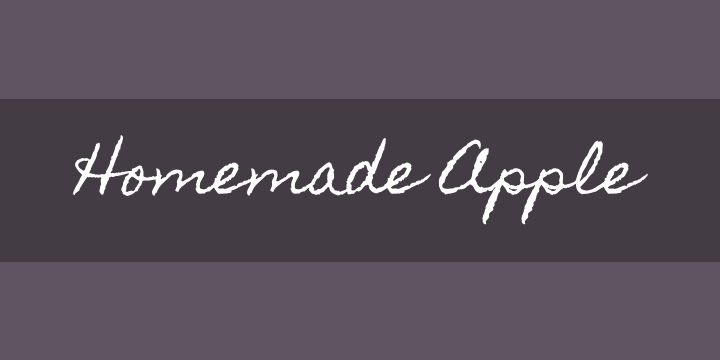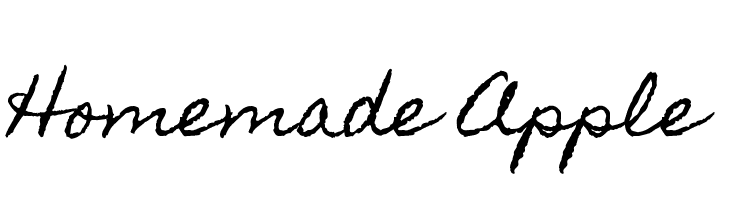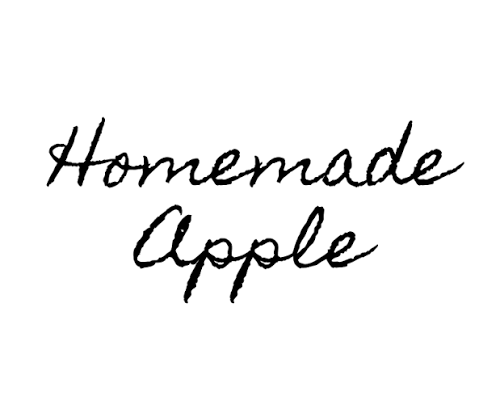
Nhiều phiên bản Homemade Apple Font trên Internet chưa được Việt hóa đầy đủ, dễ gặp tình trạng thiếu dấu tiếng Việt, sai ký tự hoặc đường nét chữ viết tay bị mất cân đối khi đưa vào thiết kế. Ngoài ra, các file font chất lượng thấp có thể làm chi tiết nét vẽ bị giảm độ sắc nét khi phóng lớn để in bao bì, tem nhãn hoặc sản phẩm nhận diện thương hiệu.
Homemade Apple font là gì?
Homemade Apple là một phông chữ thuộc dòng Script (chữ viết tay) được xây dựng dựa trên nét bút thực tế, mang phong cách mộc mạc, phóng khoáng và giàu tính cá nhân. Đặc trưng của bộ chữ này là các đường nét không quá trau chuốt, mô phỏng lại cách viết bằng bút dạ hoặc bút mực trên giấy nhám, tạo cảm giác thân thiện và gần gũi. Đây là sự lựa chọn phù hợp cho các dự án thiết kế yêu cầu tính “handmade” như nhãn mác nông sản, tiệm bánh, mỹ phẩm hữu cơ hoặc các thiệp mời mang phong cách Vintage.
Vẻ đẹp của homemade apple font nằm ở khả năng khơi gợi cảm xúc chân thành và truyền thống. Tuy nhiên, cấu trúc chữ có các nét nối tự do nên đòi hỏi quy trình xử lý kỹ thuật kỹ lưỡng khi đưa vào sản xuất thực tế. Bản việt hóa chuẩn hỗ trợ các ký tự đặc thù tiếng Việt, giúp các thông điệp trên bao bì hiển thị rõ ràng, giữ được tinh thần của bản gốc mà không gặp lỗi hiển thị dấu thanh, dấu mũ thường thấy ở các bản font chưa được tinh chỉnh.
Lưu ý: Với phong cách vẽ tay của Homemade Apple, bạn nên cân nhắc kết hợp với các tông màu trầm như nâu đất, đỏ đun hoặc xanh rêu để tôn lên vẻ đẹp cổ điển và tự nhiên của bộ chữ trên thành phẩm in ấn.
4 ứng dụng font Homemade Apple trong thiết kế và in ấn
Với phong cách chữ viết tay tự nhiên, mềm mại và gần gũi, font Homemade Apple Việt hóa phù hợp với nhiều thiết kế bao bì, tem nhãn và sản phẩm quà tặng mang tính thủ công:
- Thiết kế bao bì thực phẩm sạch và nông sản: Homemade Apple khi in trên túi giấy Kraft hoặc hộp giấy Ivory giúp sản phẩm truyền tải cảm giác mộc mạc, gần gũi và phù hợp với các thương hiệu theo hướng tự nhiên.
- Sản xuất tem nhãn decal sản phẩm Handmade: Font chữ viết tay này phù hợp cho nhãn dán hũ mứt, nến thơm, xà phòng thủ công hoặc các sản phẩm cá nhân hóa, tạo điểm nhấn riêng cho thương hiệu.
- In thiệp cảm ơn và voucher tri ân: Những thông điệp ngắn sử dụng Homemade Apple giúp các mẫu thiệp, thẻ quà tặng trở nên thân thiện và giàu cảm xúc hơn.
- Trang trí hộp quà tặng đặc sản: Khi kết hợp cùng họa tiết minh họa thủ công, Homemade Apple giúp bao bì tạo cảm giác đồng bộ và thể hiện phong cách riêng của sản phẩm.
4 lưu ý khi sử dụng font chữ Homemade Apple
Để font Homemade Apple Việt hóa giữ được nét chữ viết tay khi ứng dụng vào thiết kế và in ấn, designer cần chú ý:
- Kiểm soát độ mảnh của nét chữ: Homemade Apple có các nét bút thanh và mềm. Khi in trên giấy Kraft hoặc chất liệu có độ hút mực cao, nên điều chỉnh độ dày nét phù hợp để hạn chế mất chi tiết.
- Tối ưu đường Path khi gia công bế nổi: Chuyển đổi font Homemade Apple sang dạng vector giúp xử lý các đường cong uốn lượn chính xác hơn, hỗ trợ quá trình dập nổi logo hoặc tên thương hiệu trên hộp quà.
- Lựa chọn kích thước chữ phù hợp: Do có phong cách Script viết tay, Homemade Apple nên ưu tiên sử dụng cho logo, tiêu đề hoặc thông điệp ngắn thay vì các đoạn nội dung dài để giữ khả năng đọc.
- Kiểm tra vị trí dấu tiếng Việt: Các ký tự có dấu cần được rà soát trước khi in để đảm bảo dấu thanh không bị chạm vào nét chữ hoặc làm mất cân đối bố cục.